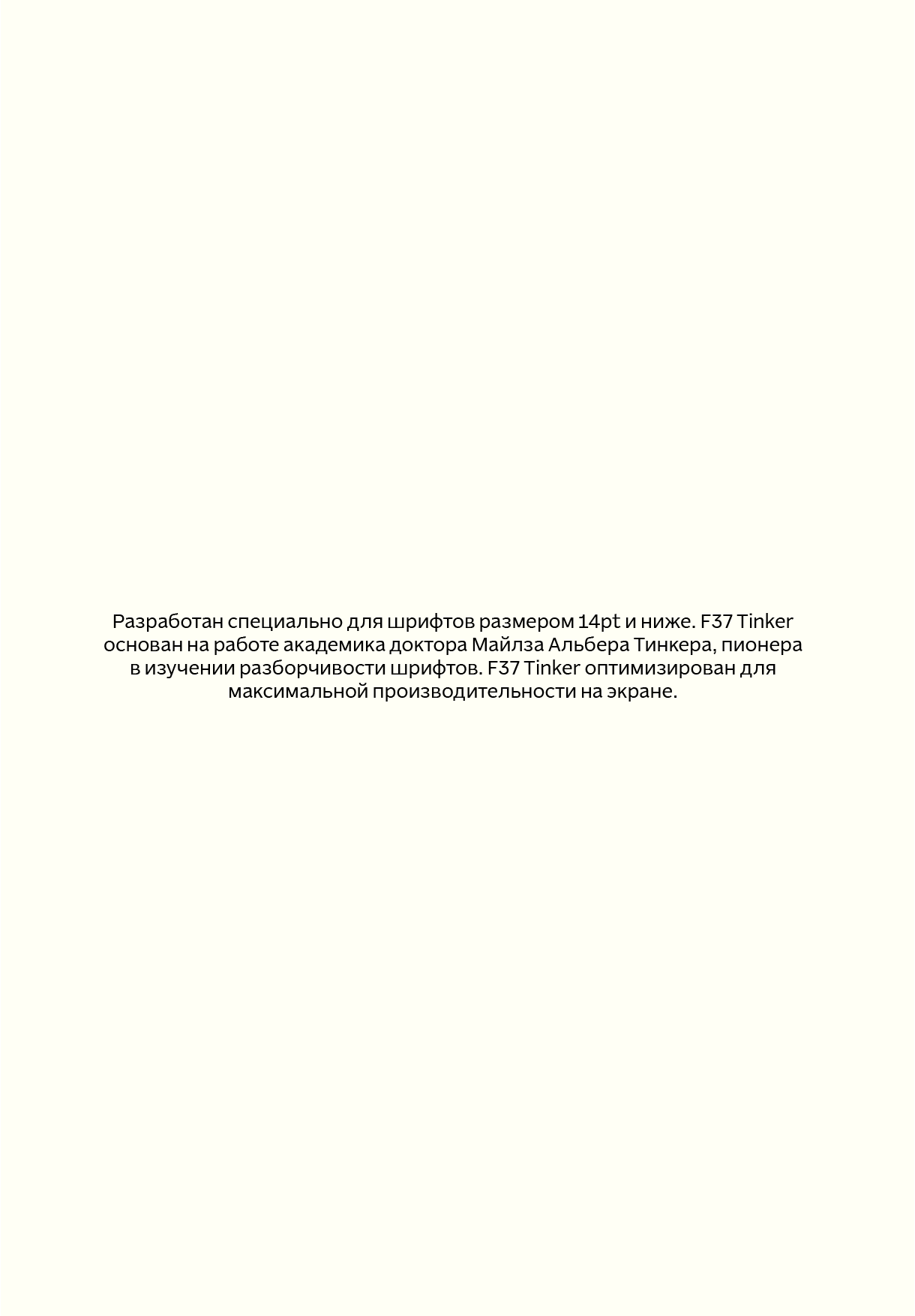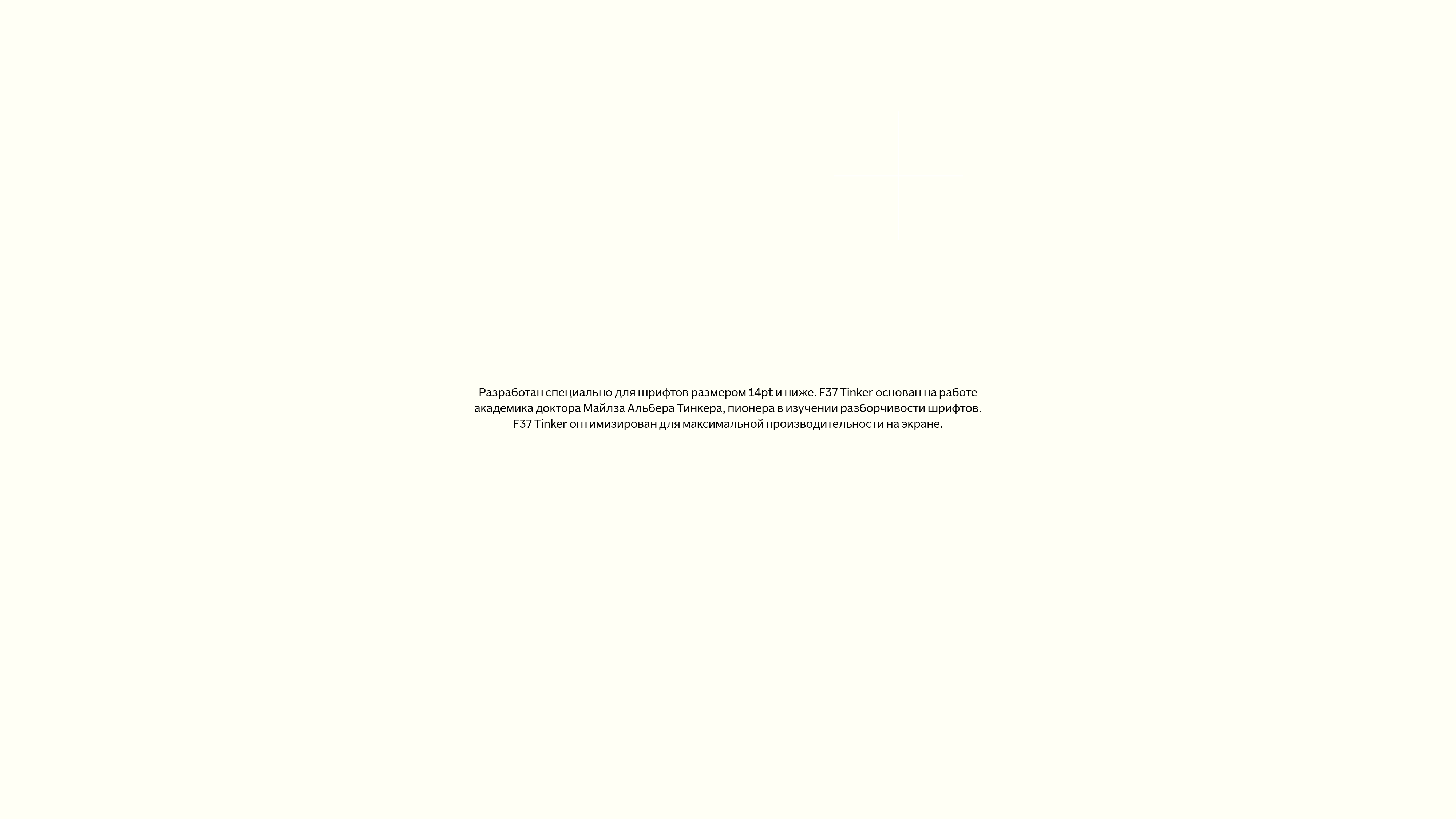
F37 Tinker Cyrillic Font Sampler
F37 Tinker — це наша шана впливовому американському письменнику та вченому доктору Майлзу Альберту Тінкеру, піонеру у вивченні розбірливості шрифту.